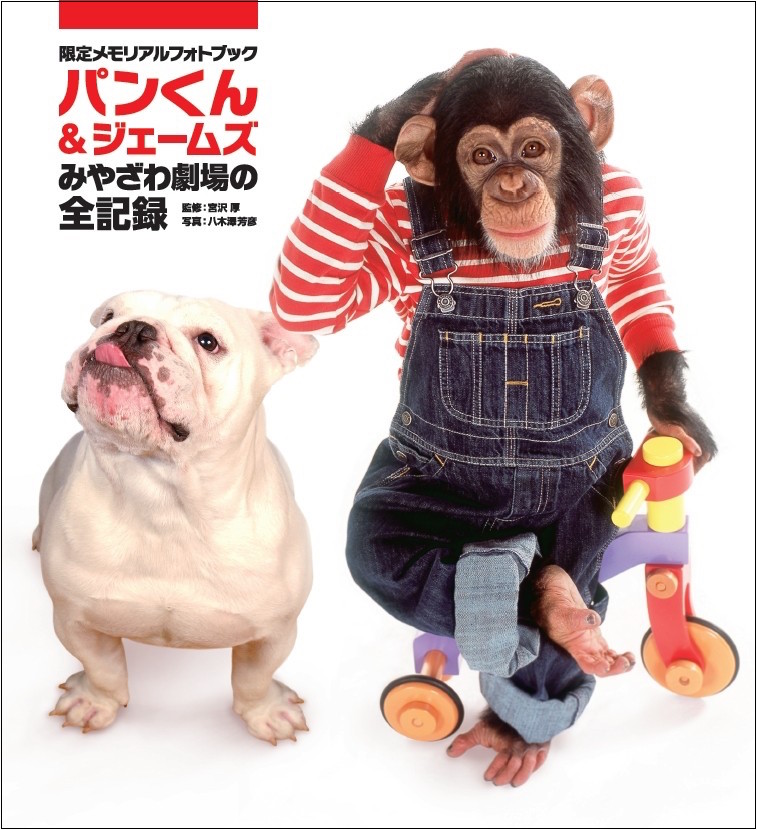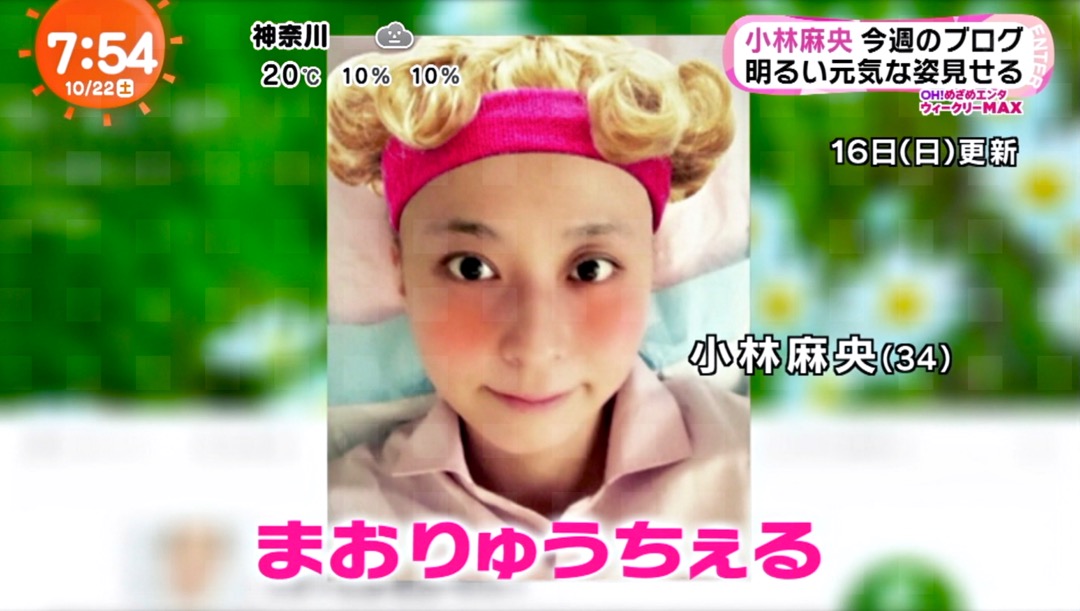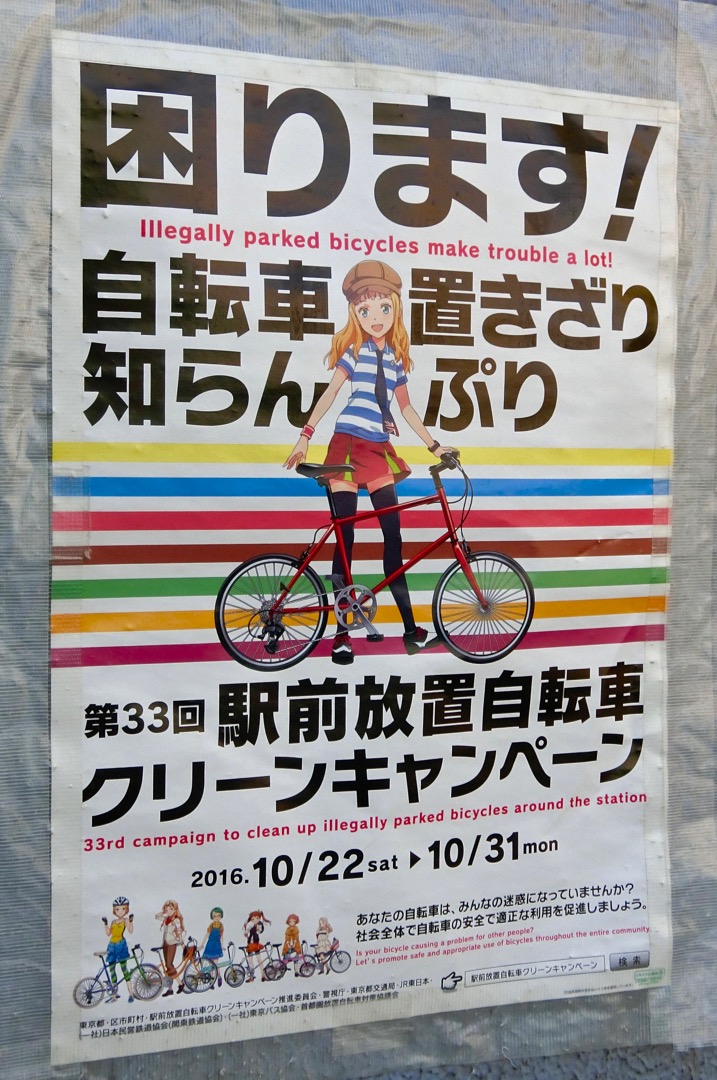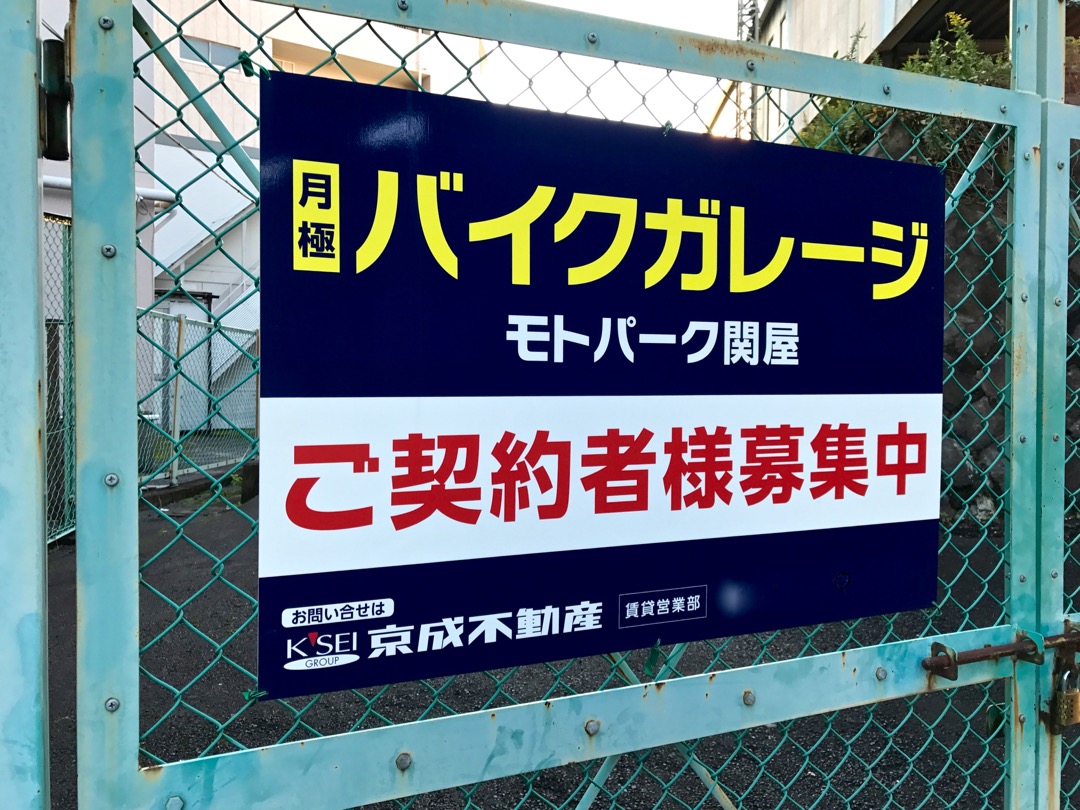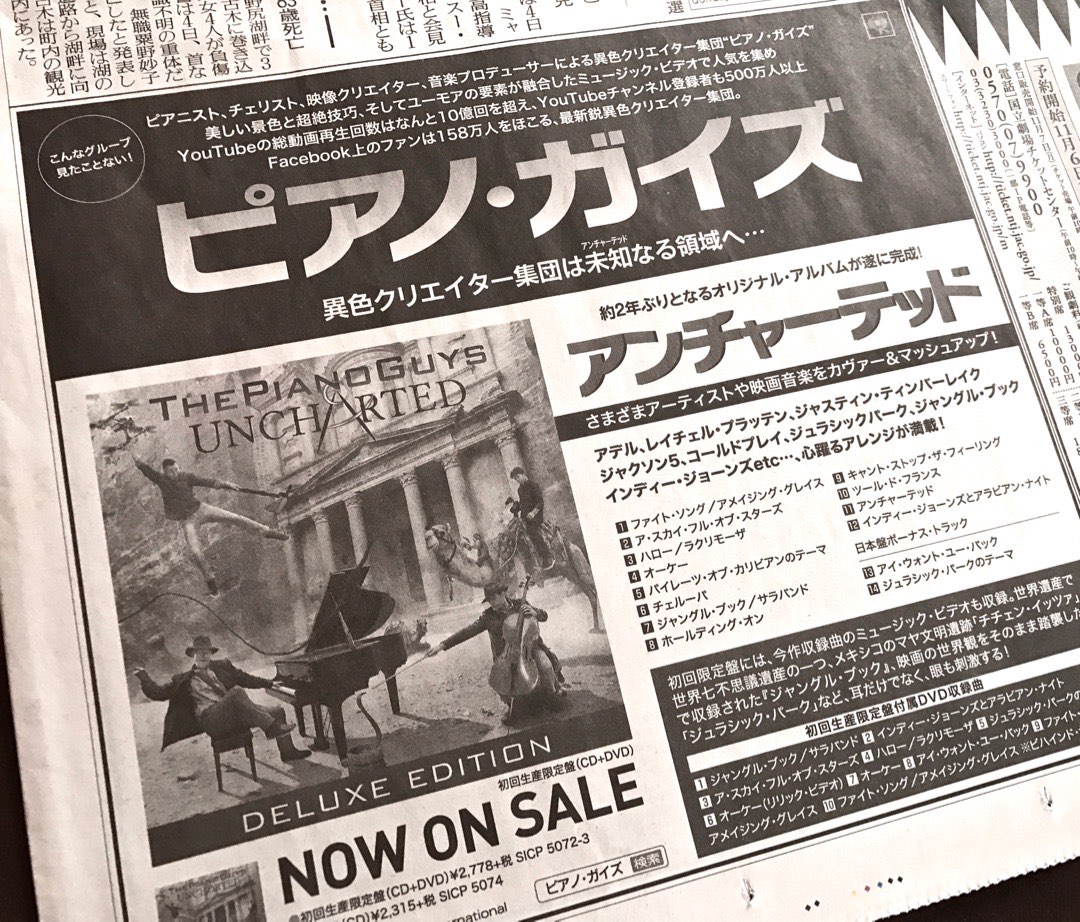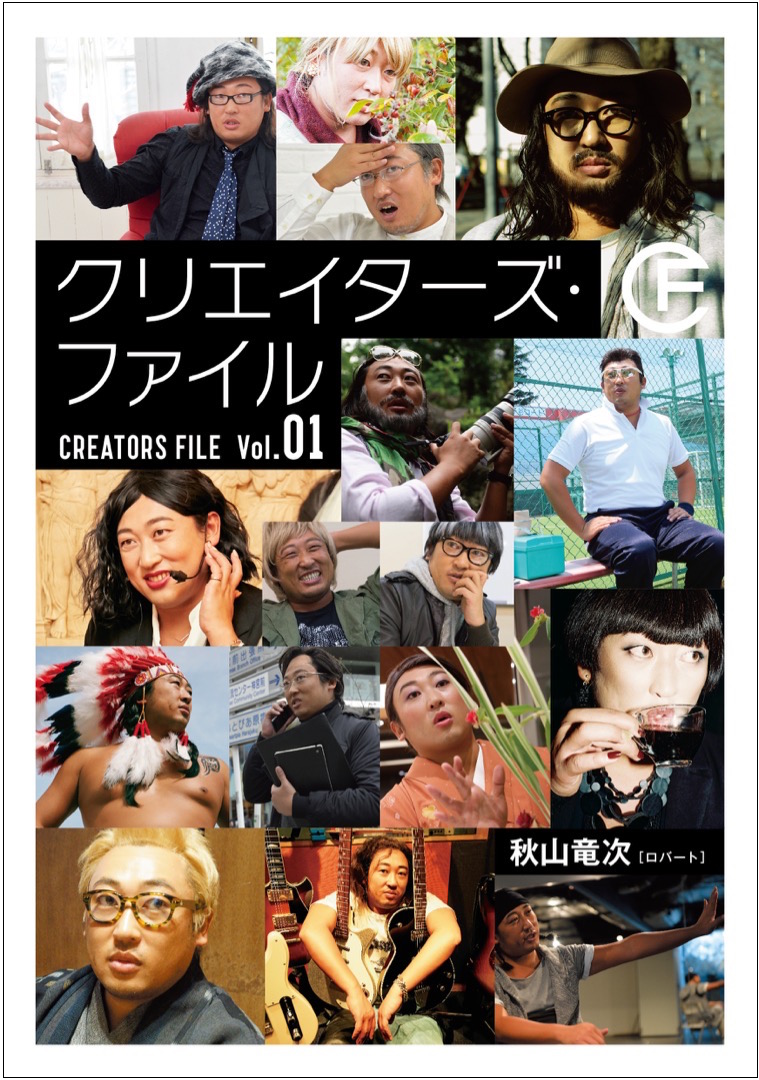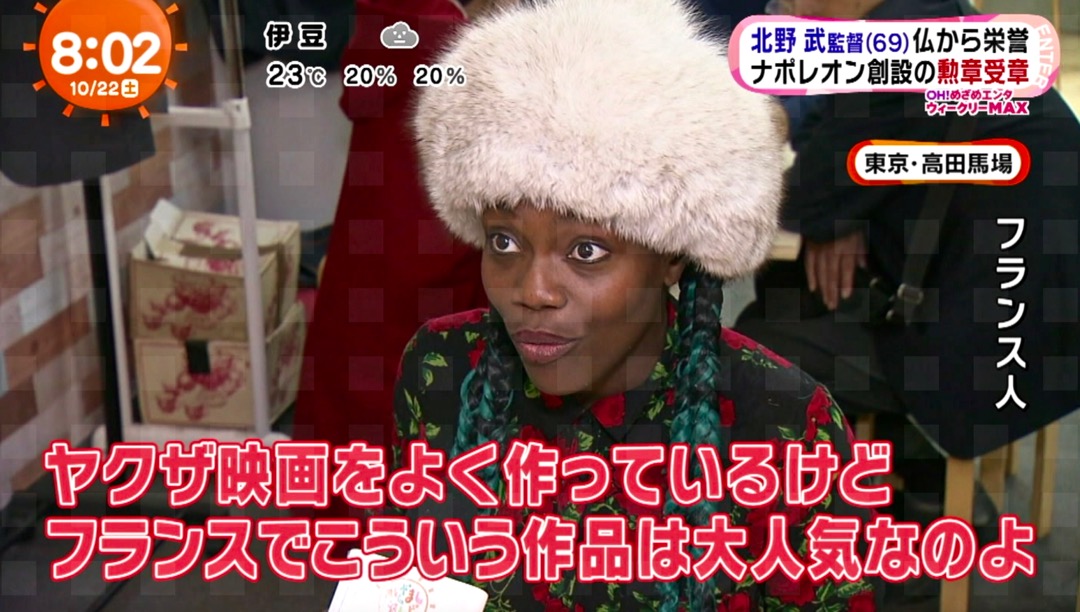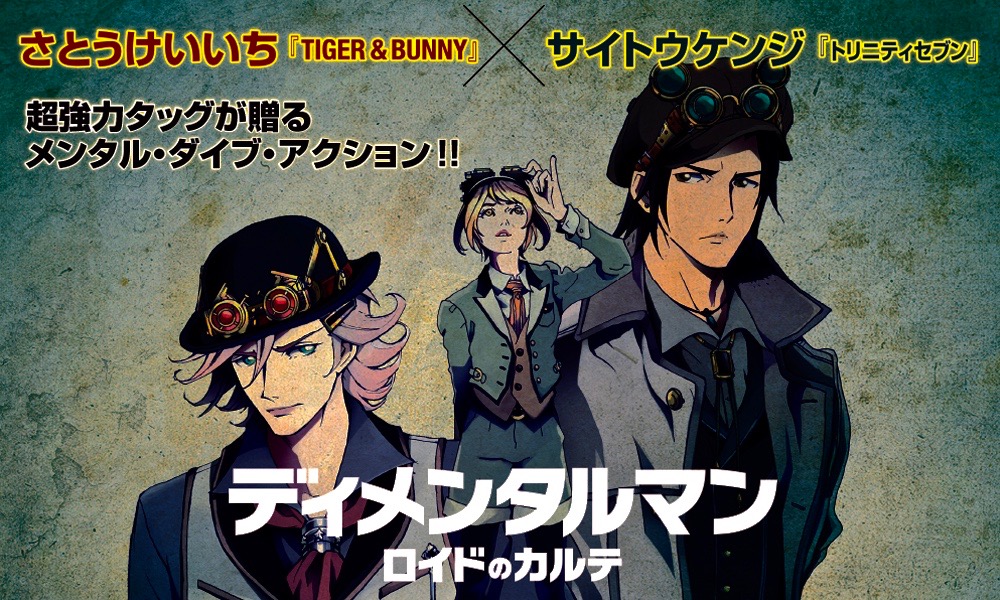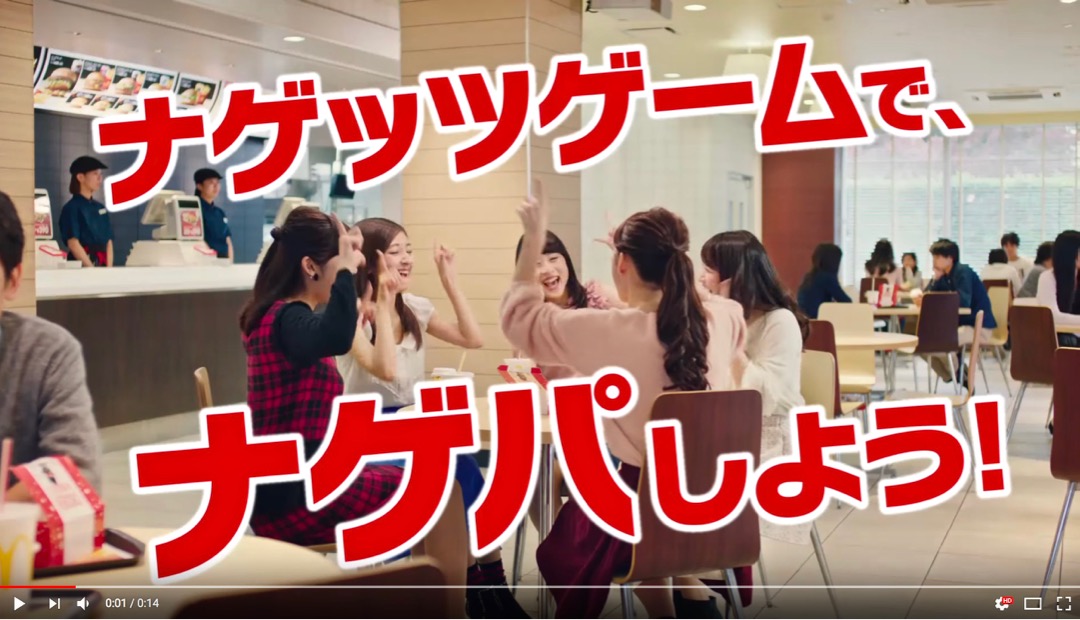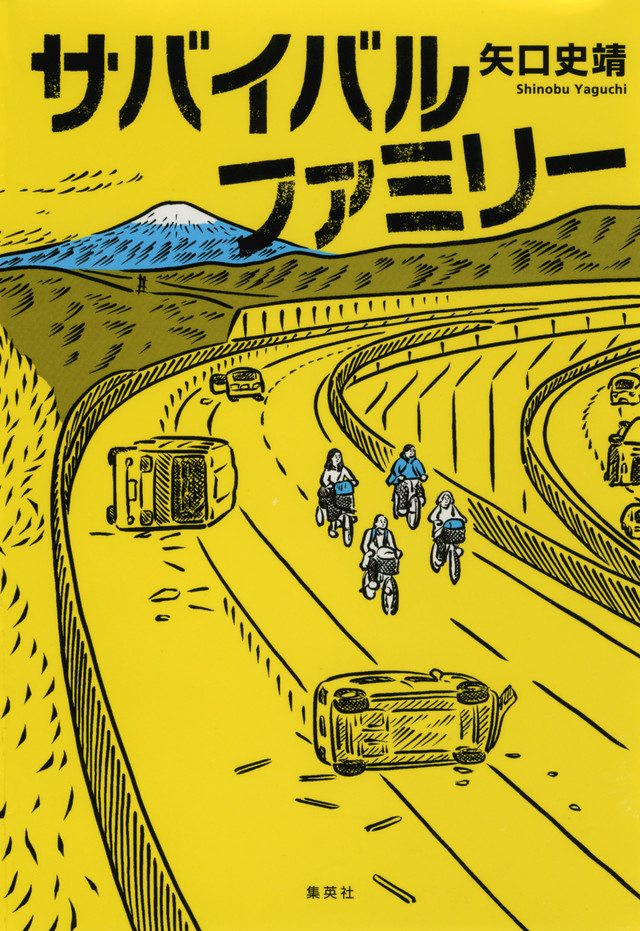
書名:おいしい犬ごはん
著者:羽尾健一、羽尾理恵子
発行:日本文芸社
書名:はじめてのクルーズ
著者:クルーズ編集部
発行:海事プレス社
無料版・商品版とも、
NEC特殊文字とIBM拡張文字も使えるようになってアップデートしました。
←サンプルです。
ニタラゴルイカフォント、無事アップデートできました。
拡張文字はちゃんと入力できましたし、ダーシも繋がりました。
来月のわんぱくルイカも楽しみにしています。
昨年の秋から始まったルイカ系拡張文字の制作企画。
来月、わんぱくルイカフォントをアップデートすれば、終了です…。
「ポケモン公式YouTubeチャンネル」よりアップされている、ポケモンのパペットアニメ『パペモン』でニタラゴが使われていました。↓
もう1枚。
やっぱり数字の「1」で判別できますね。
ニタラゴルイカの、ウェイト03辺りでしょうか。
文字の背景が暗くシンプルなので、このくらいの太さがキレイで読みやすいですね…。
書名:ハムシハンドブック
著者:尾園暁
発行:文一総合出版
同じシリーズのようだ。
書名:オタマジャクシハンドブック
著者:松井正文、関慎太郎
発行:文一総合出版
書名:ゲンゴロウ・ガムシ・ミズスマシ ハンドブック
著者:三田村敏正、平澤 桂
発行:文一総合出版
書名:タガメ・ミズムシ・アメンボ ハンドブック
著者:三田村敏正、平澤 桂
発行:文一総合出版
CMも放映中のようですが、スマホで遊べる、『A3!』(エースリー)という女性向けイケメン役者育成ゲーム(だそうです)でニタラゴルイカが使われています。
かなり貴重な使用例だと思います。
ゲーム内で名前やプロフィールなどを入力する欄があり、ユーザーが文字を入力すると、その入力した文字がニタラゴルイカで表示されますので、組み込みでの使用で間違いないはずです。
takumiさんからの報告があってすぐに、私もアプリをインストールして確認しました。
上記takumiさんの追加情報のように、
このアプリでは、画像化(アウトライン化含む)しての使用ではなく、フォントを組み込んでいると確信できる表示がありましたので、すぐに相手に連絡を取り、現在「フォント組込み使用許諾契約書」の手続きが進行中です。
完了したら、またここで報告いたします。
契約完了  さとうゆたか  2017年8月10日(木) 13:42 [修正]
本日の午前中に「フォント組込み使用許諾契約書」の手続きが完了いたしました。
互いに会う必要もなく、申請メールと契約書のダウンロード購入だけで完了する、タイプラボの「フォント組込み使用許諾契約書」は、スグレモノ。
↓
http://www.dlmarket.jp/products/detail/89447
↑使用報告から、たった1日半で、すべての手続きが終わりました。
お疲れ様です  takumi  2017年8月10日(木) 17:30  HP [修正]
佐藤さん、お疲れ様です。
とりあえず、一件落着したようで安心しました(後味は良くありませんが)。
一応商品版を使っていた所を見ると、商品版を買ってくれた所までは良かったけど、使用者が使用条件の確認を怠っていて、勝手に組み込みに使用されてしまった…と言った所でしょうか。
フォント作者がどんなに訴えかけても、知らない場所で勝手な使われ方をしていたり、到底、作者はそれに気付くことができなかったり、それを教えてくれるユーザーもいなかったり…。
フォントに著作権がある、という認識がそもそも広まっていないために、フォント作者もフォントベンダーも弱い立場だな…と思います。
夢をかなえる人の  さとうゆたか  2017年8月5日(土) 9:32
書名:シンクロニシティ・マネジメント
著者:堀内恭隆
発行:サンマーク出版
ウサギの飼育ガイド  さとうゆたか  2017年7月30日(日) 16:15
書名:ネザーランドドワーフ
著者:大野瑞絵
発行:誠文堂新光社
家電量販店の広告媒体  takumi  2017年7月24日(月) 21:29  HP
佐藤さん、こんばんは。
Instagramにも投稿しましたが、エディオンに行った際、展示品の冷蔵庫の中にあった牛乳パック(サンプル、広告媒体)でニタラゴルイカが使われていました。
使用場所はマニアックかもしれませんが、本家本元ニタラゴルイカの使用例は貴重だと思うので、ここにも上げておきますね。
takumi  2017年7月24日(月) 21:29  HP [修正]
これは裏面。
takumi  2017年7月24日(月) 21:30  HP [修正]
もう1枚だけ。パック上部でも。
さとうゆたか  2017年7月25日(火) 8:14 [修正]
takumiさん、いつも投稿ありがとう!
冷蔵庫の中の宣伝媒体ですか〜。
地味なところから、じわじわと使用例が増えていくといいんですけどね…。
ポスター  さとうゆたか  2017年7月24日(月) 16:12
スマホ・スタンプラリーだそうです。
http://www.driveplaza.com/special/hokkaido_stamprally2017/
さとうゆたか  2017年7月24日(月) 16:14 [修正]
これは前回のもの。